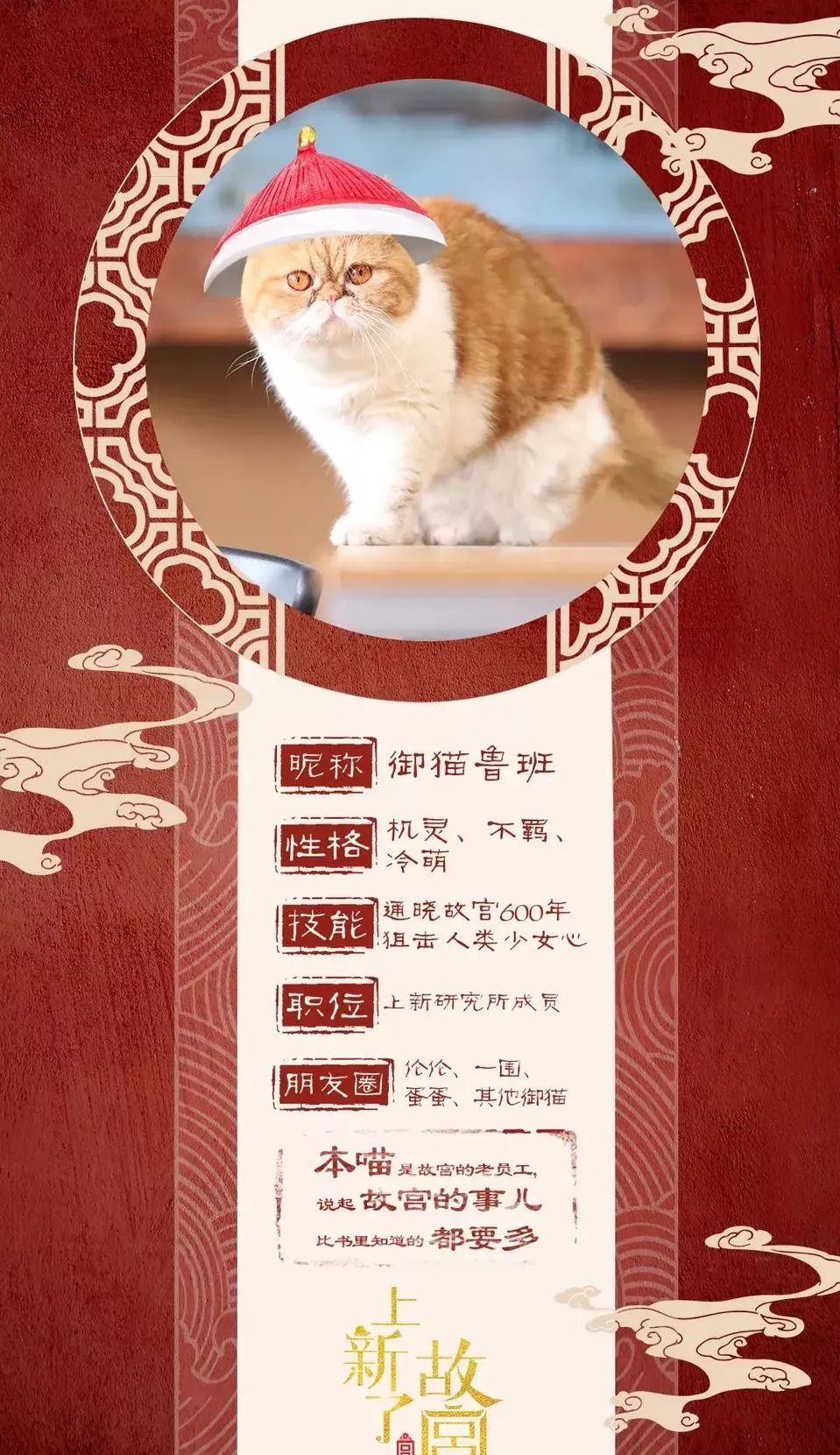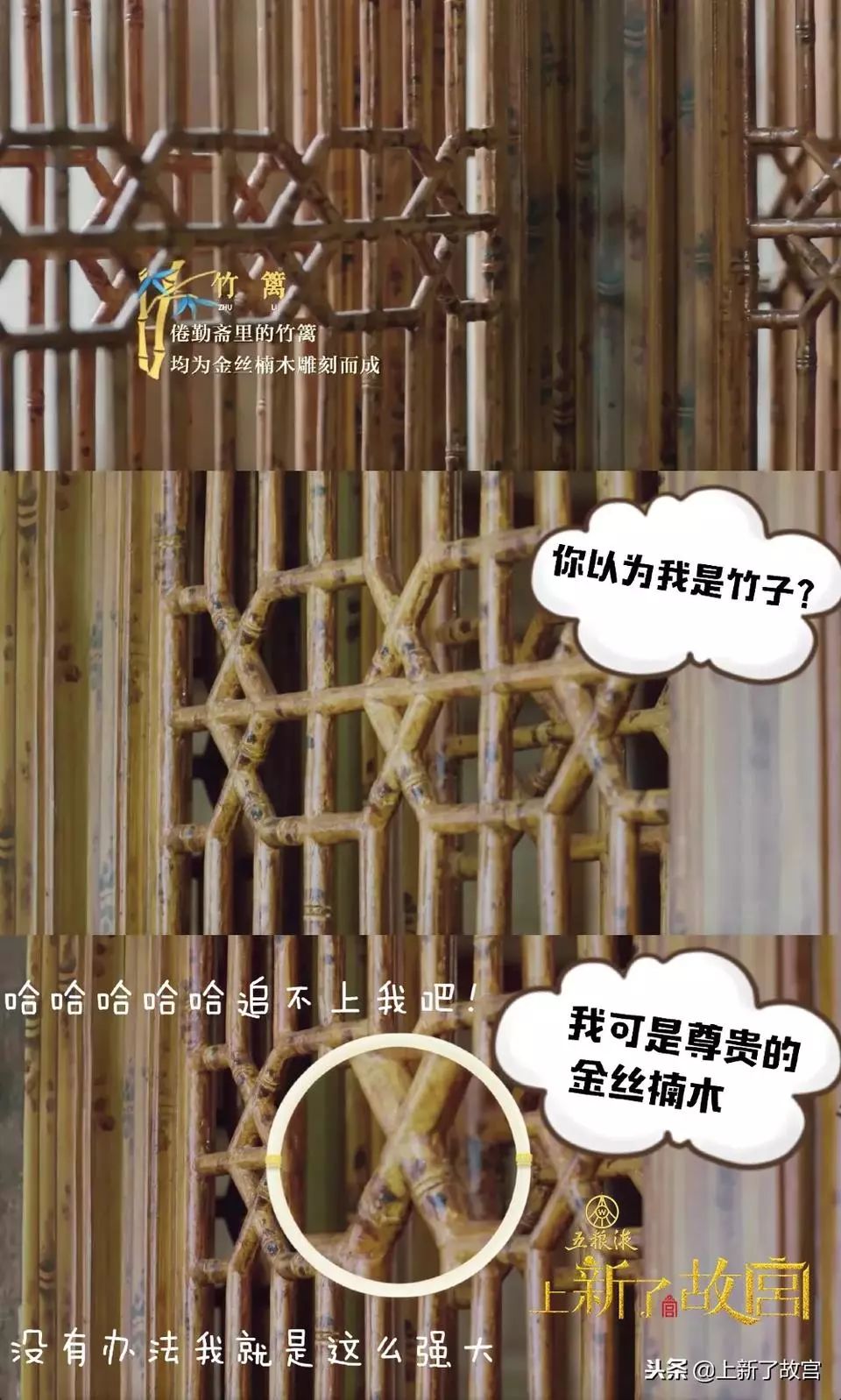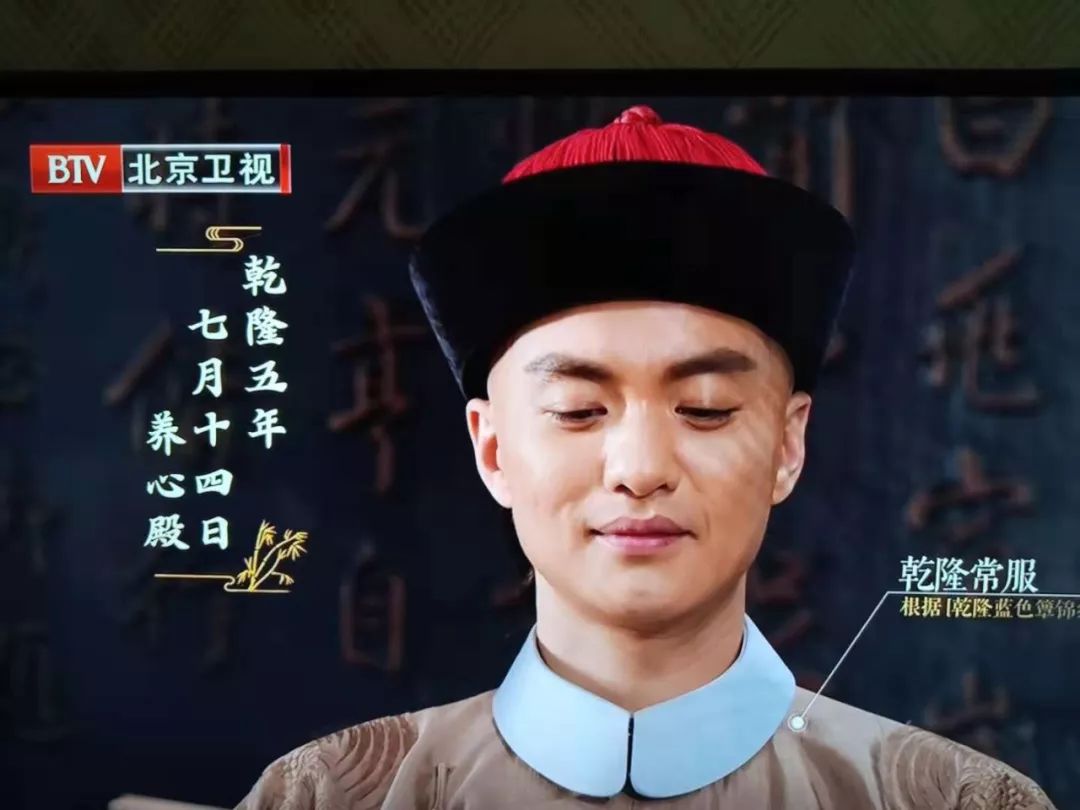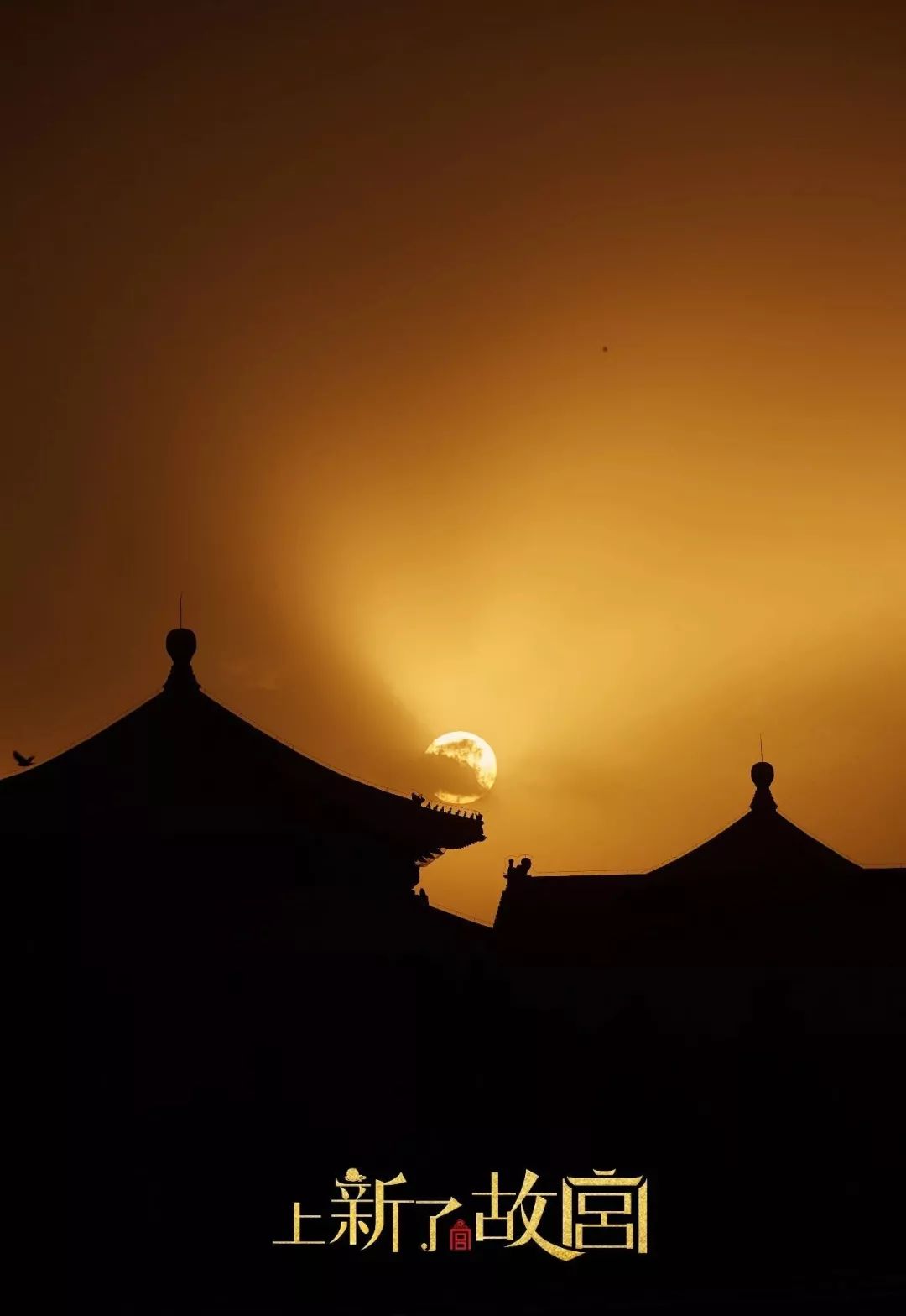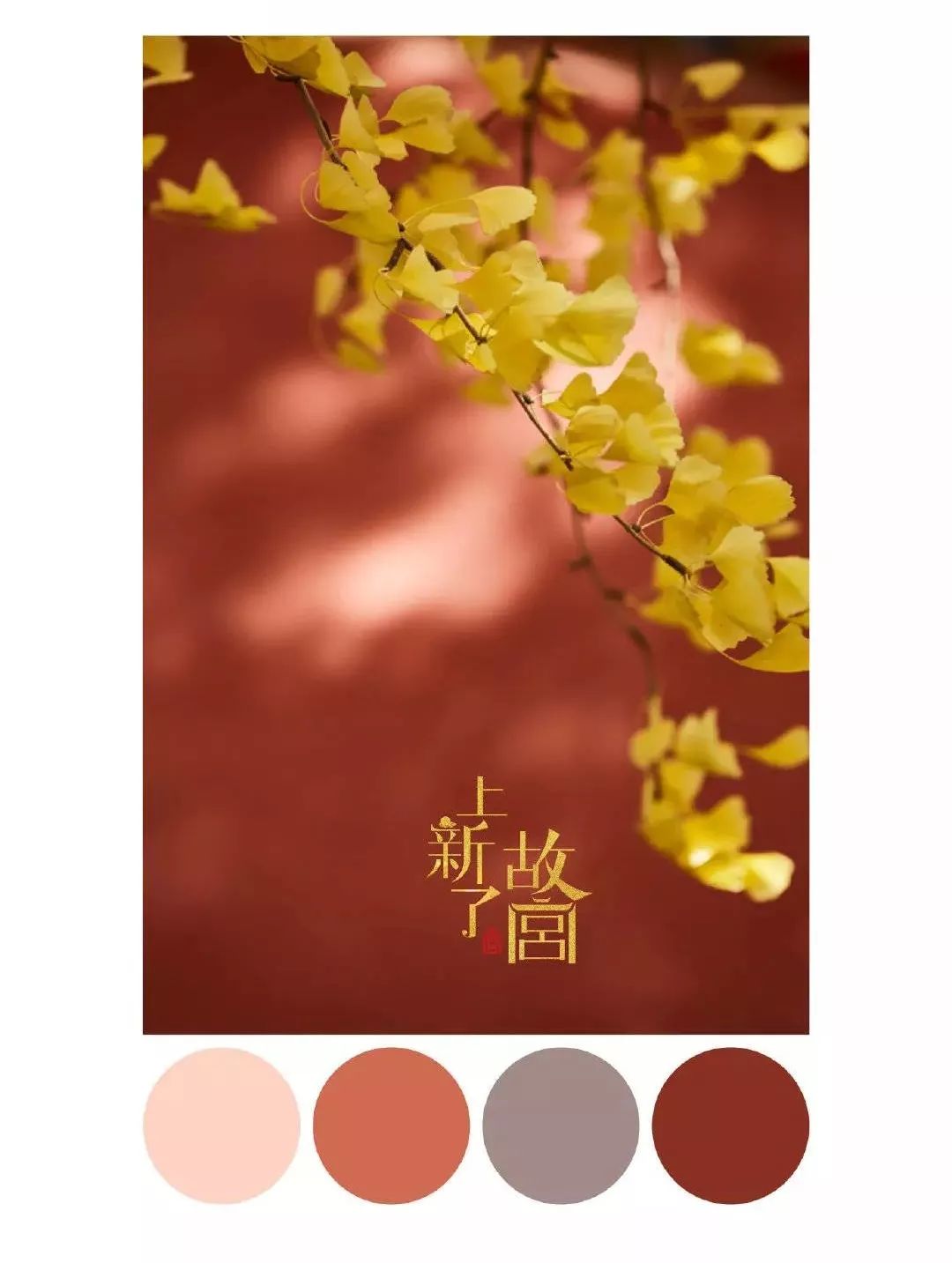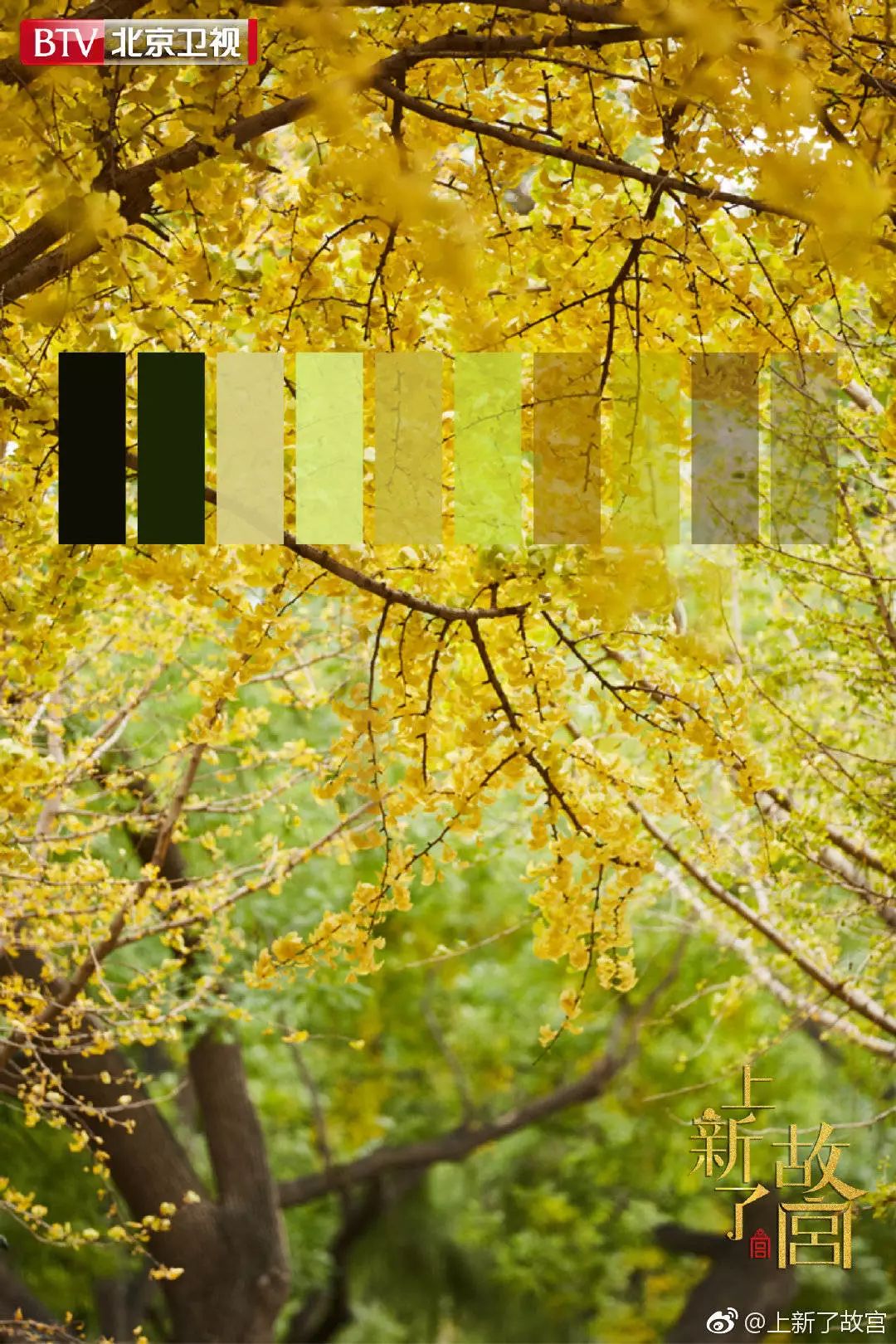
从邓伦的颜,到鲁班的萌,这部综艺凭啥让你欲罢不能?
之前一直听说《上新了故宫》口碑炸裂、收视逆天什么的,但一直没机会看,正好周末播到孝庄和顺治,让我勾起了对宁静版大玉儿的回忆(一不小心暴露了年龄)。
不得不说,确实戏好,难道这是故宫版秘史?然后我又去追了前面四期,发现里面水太深了,一进去,就出不来了,哈哈!
让你舔屏的偶像剧
虽然每周都有女演员客串,但我知道大部分都是冲着邓伦的颜去的(别不承认),我也是,小哥哥确实是行走的画报啊,每期都换着大衣po照,看得人春心荡漾~
你确定不是来走秀,拍偶像剧的嘛?摄影师也太偏心了,前方高能,千万要淡定……
让你想吸的萌宠纪录片
不过奶伦再有魅力,也抵不过《上新了故宫》里绝对的主角,看到他对它放电了么,多少人想做那只猫,举手!
伦家才不稀罕,本喵可是正儿八经有名字、有族谱的,还有满肚子你不知道的货哦(确实肉肉挺多)~
不过柚子最喜欢的就是它的小尾巴,撩得人不要不要的,还能变换多种方式,这是装了发动机嘛?
作为御猫,鲁班不仅会卖萌,还能游遍故宫的各个角度,给我们科普小知识,真是腻害了。
让你停不下来的宫廷剧
如果说奶伦负责颜值,鲁班负责卖萌,那周一围就负责刷剧了,因为他现代的样子,真的很像金星,有木有?
看看这老干部的走秀架势,嗯,离鬼怪还差那么两围、三围……
可一旦换上古装,立马不一样了,满眼都是戏,围哥怕是从过去穿越来的吧?
每一期都有他,爸爸演完,演儿子,整部故宫的皇帝都被他承包了。
服装造型也是格外用心,都是根据史料画像还原的,所以那些弹幕里说什么穿得像太监的,一定是清宫剧看多了,皇帝也是人,还不允许人家穿个居家服啥的啊!
让你好奇的探秘剧
抛开主角不谈,还有一个让你对这部综艺不肯换台的原因,那就是能看到好多未开放区域,像是考古探险一样。
从乾隆的私人戏台倦勤斋,让人惊叹木头也可以做成竹子,天花板也能做出裸眼3D感。
到符望阁设计巧思的房间和藻井,让我对大猪蹄子有了新的改观,当设计师相当有天分啊!
之后的畅音阁也是机关重重,吊威亚,水池聚音,都是跪服orz。
就连净化身心的浴德堂,看起来也很有(像)异(做)域(实)风(验)情(的)。
让你进入氛围的字体
有没有发现,《上新了故宫》不像别的综艺,全是各种花字、二次元,能记住的不多,它基本选择了一种字体,汉仪北魏写经,字由上也有哦。
上周五找孝庄线索的时候,有它。
乾隆看奏折时,有它。
娘娘说搞笑的港普时,也有它。
伦伦研究历史资料时,当然也离不开它。
鲁班更是要御用字体啦,喵~
还根据不同的语境,加了小元素,很有代入感,要给后期加鸡腿。
除了汉仪北魏写经,它还用了其它字体,像火得不能再火的汉仪尚巍手书。
还有这种古今对话的表情包,让有一种穿越感~
我找了两款相似字体,都很有古典美。
logo也不得不说,“宫”字像宫殿一样、庄严,大气,“新”上的那一点,像腾云驾雾一样有仙气,中间那个印章宫,更是告诉你们这是如假包换的故宫文创,别买错了,哈哈!
单放也很好看,在夕阳下,折射出历史的沧桑感。
转起来更有立体感,伦伦都忍不住看了一眼~
让你张张截屏的色彩
高能的故宫当然不止这些,不然怎么那么多人想去故宫扫地,还不是为了那独一无二的风,做成屏保美如画,提取色卡更是满满的艺术感。
最后知道你们惦记本喵皇,
赏你们几个表情包吧!